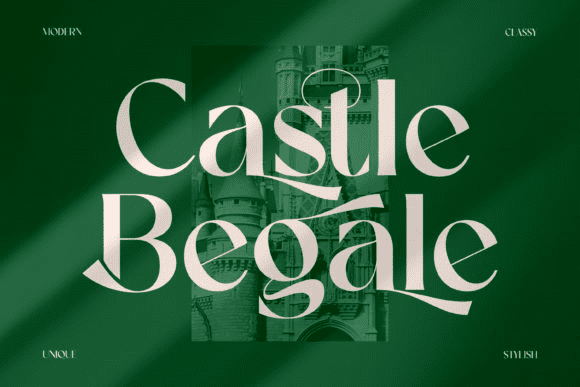
Название: Castle Begale Font (2021)
Castle Begale - стильный, стильный и современный шрифт с засечками.
Castle Begale закодирован PUA, что означает, что вы можете легко получить доступ ко всем глифам и штрихам!